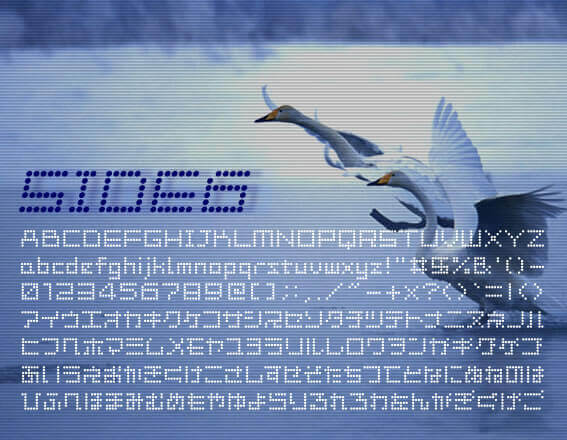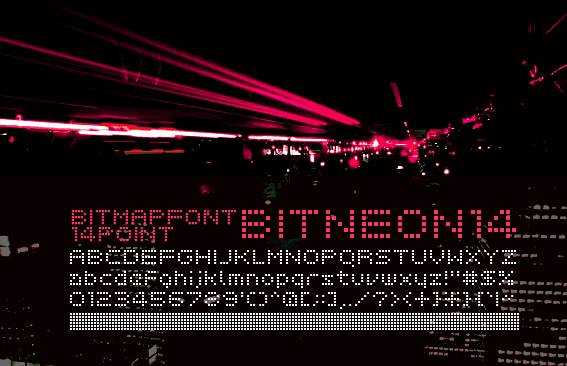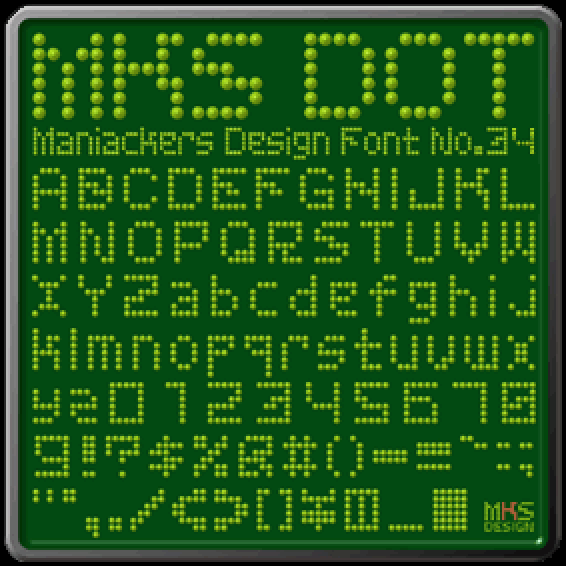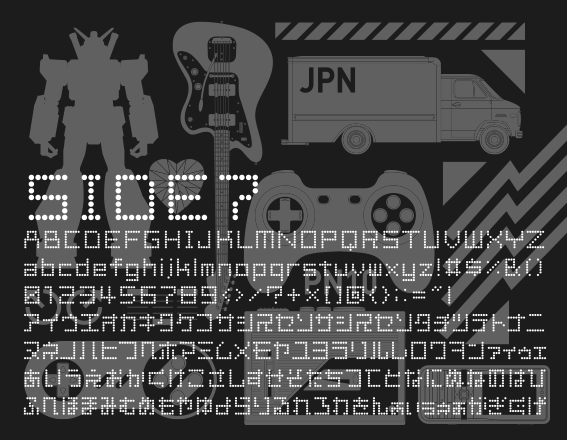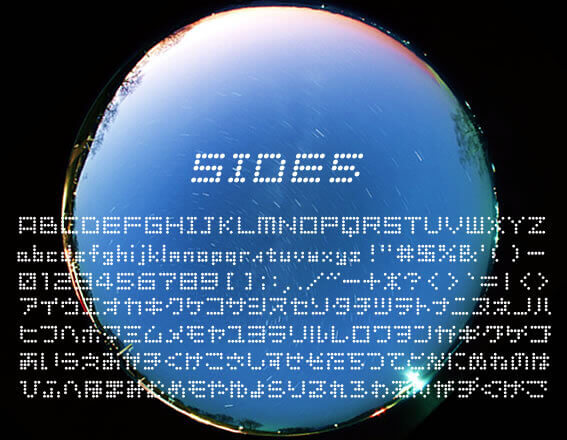
無料ダウンロードできるドットフォント16選
ファミコンでも使われていそうな無料のドットフォントを16つまとめました。基本、個人利用であればフリーでダウンロード可能です。中には日本語も使えるフォントもあるので幅広くご利用いただけます。
BLOCK block
キューブを組み合わせて表現されたフォント。
Building 2-AL, KT
高層ビルの部屋の明かりを利用して絵を作っているのをイメージして作られたフォント。
Dotted
フォント名の通り、ドット状フォント。
MKS Dot-AL
かわいらしい丸でデザインされたドットフォント。
PowerBALL
光る珠を集めた文字。
サイド5フォント
flopdesign様よりダウンロードできるひらがなも使えるドットフォント。
サイド6
上記と同様、flopdesign様よりダウンロードできるドットフォント第2弾。
サイド7フォント
上記と同様、flopdesign様よりダウンロードできるドットフォント第3弾。
デジットフォント
デジタルチックにデザインされたフォント。
てんてん
フォント名の通り、点で表現されたフォント。
テンテンフォント
独特な表現方法のドットフォント。
ピクトプラズマ
ドットで表現されたピクトグラムフォント。
ビットネオンフォント
四角で表現したビットマップフォント。
まん丸ちゃん
昔の神宮球場や、地方野球場にある電光掲示板の温かみのある光を出せるフォント。
池袋西武の1階でぐるぐる回ってる数字
池袋西武の1階でぐるぐる回ってる数字フォント。
競馬場電光掲示板フォント:ギャロップダービー
競馬場の電光掲示板の数字を入れたフォント。